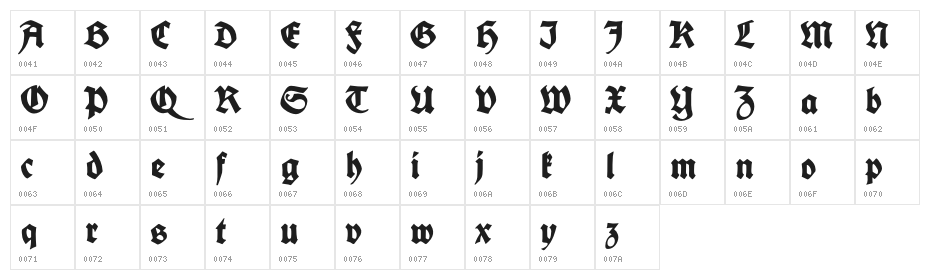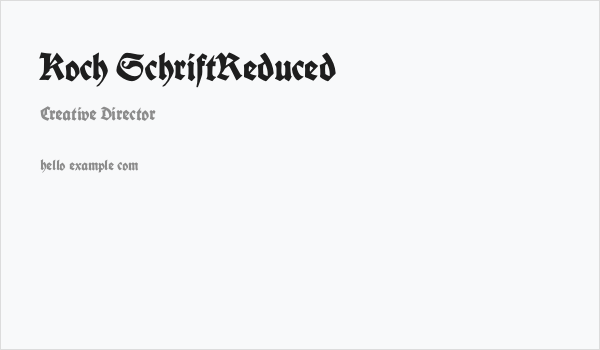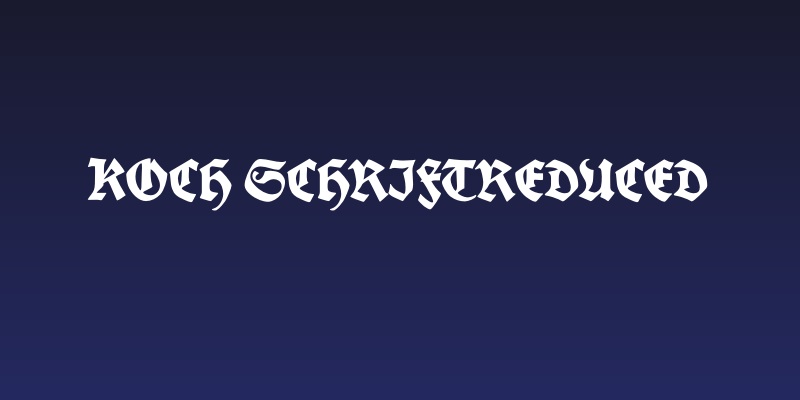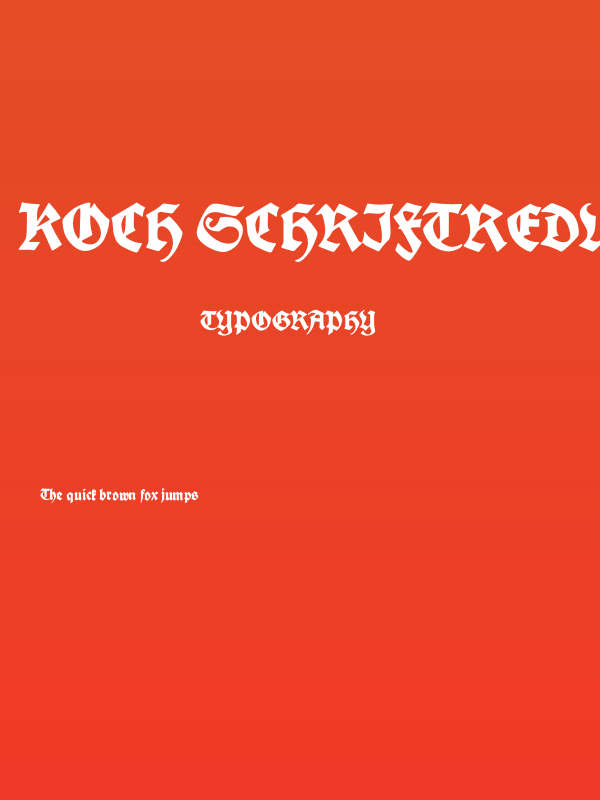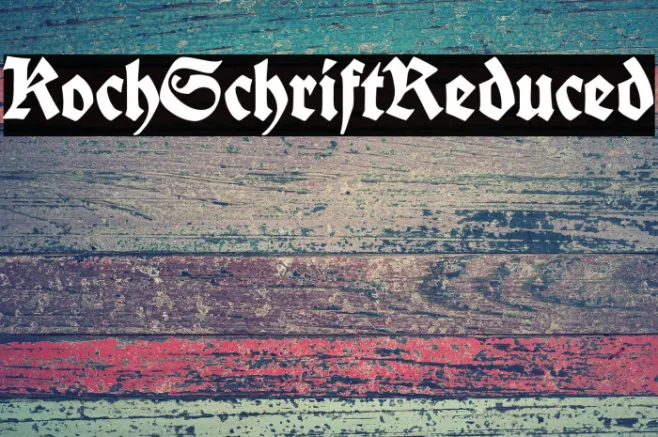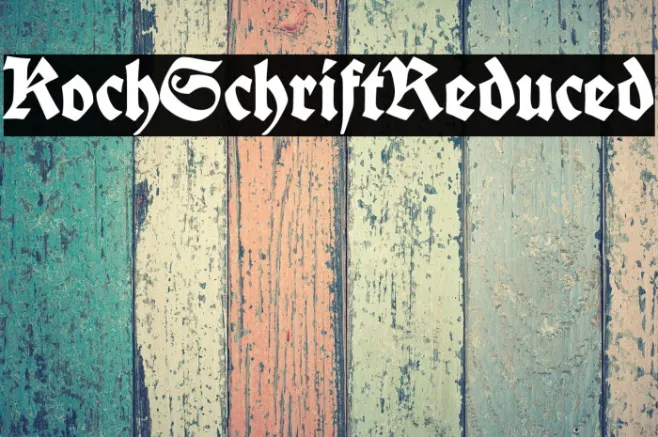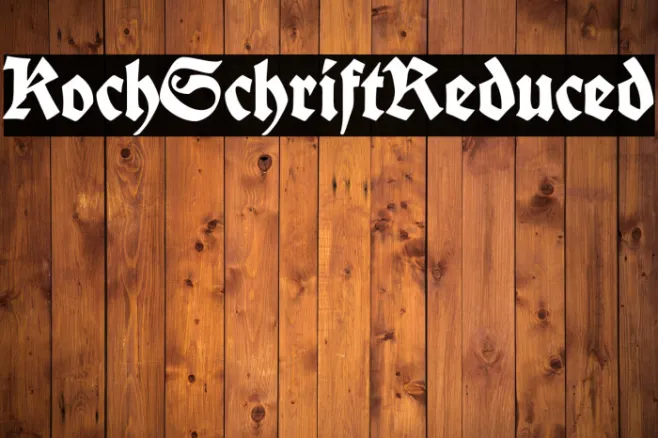
Koch-SchriftReduced Font
✎ Gothic
| Famille de police | Koch-Schrift Reduced |
| Catégories | Gothic |
| Projets proposés | Ideal for projects requiring a historical or gothic aesthetic, such as book covers, posters, or branding for vintage-themed products. |